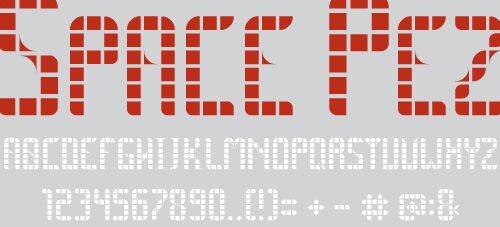
Space Pez Outline von Nils von Blanc ist eine kostenlose, retro-futuristische Digital-Display-Schrift, deren Look an ein abgerundetes Raster erinnert, das in die Versalien eingebettet ist. Die Buchstaben wirken wie eine Beschilderung aus der Space-Age-Ära, etwa wie bei alten Arcade-Automaten oder Sci-Fi-Titelsequenzen, wobei die konturierten Striche in saubere, rechteckige Zellen unterteilt sind. Die weichen Kurven verleihen der Geometrie dabei einen verspielten statt strengen Charakter.
Diese kostenlose Schrift eignet sich perfekt für Plakatüberschriften, Album-Cover, Gaming-Branding, Event-Flyer und Titelkarten, bei denen ein codierter, modularer Rhythmus schnell für visuelle Wirkung sorgt. Sie passt auch hervorragend zu kurzen Cover-Lines und Monogrammen, da das segmentierte Outline-Design selbst wenigen Buchstaben eine klare, blockartige Präsenz verleiht.
SPACE PEZ by Nils von Blanc